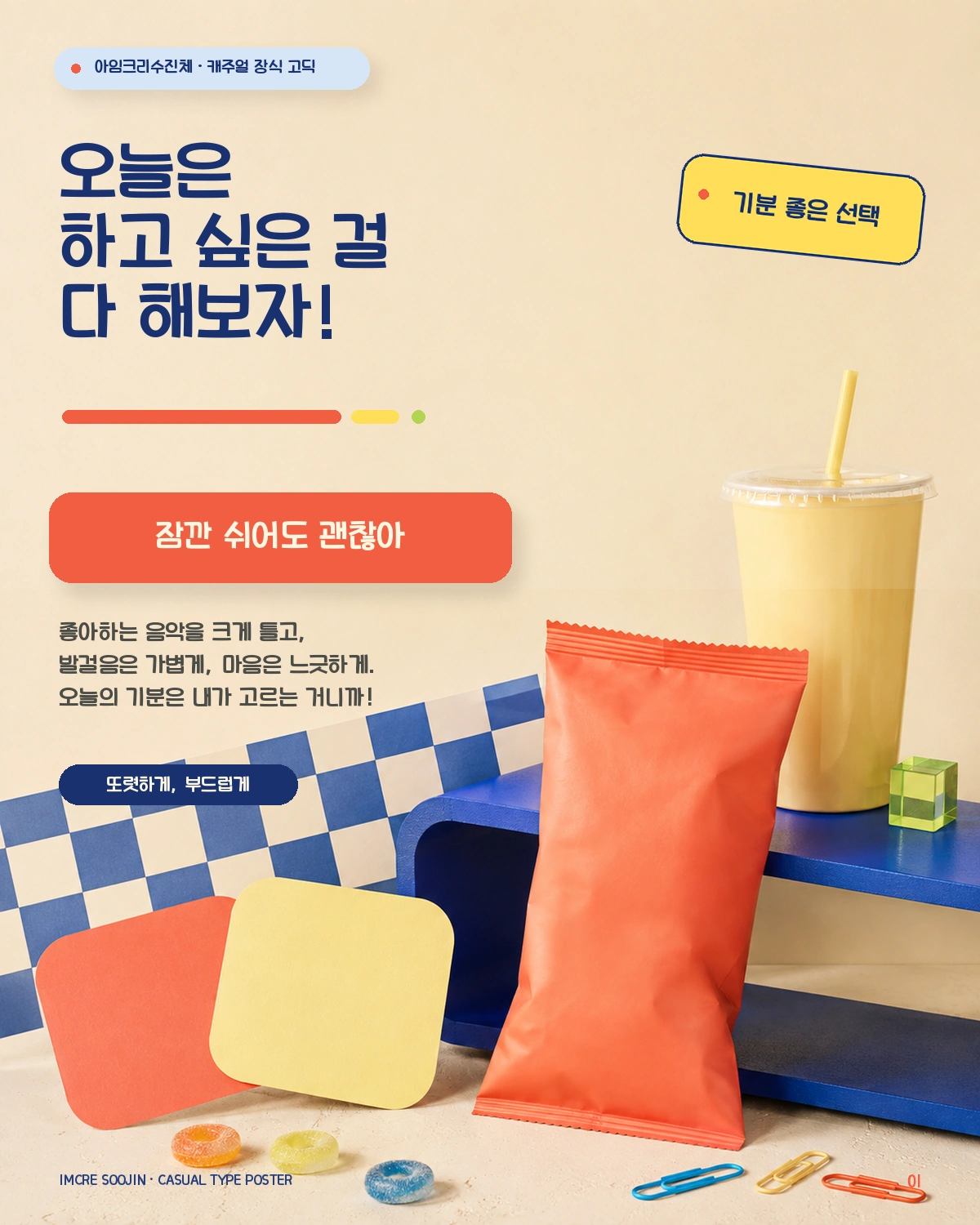
아임크리수진체 — 발렌타인드림에서 배포하는 무료 폰트입니다. 네모난 골격에 둥근 모서리를 더해 또렷하면서도 부드러운 인상을 주는 장식 고딕체
영상 디자인 스튜디오 발렌타인드림이 자사 앱의 전용서체로 만들어 2020년에 무료로 푼 서체입니다. 폰트 파일 안에는 저작권자가 발렌타인드림, 서체 설계는 와이즈폰트로 적혀 있습니다.
이름의 앞부분이 그 앱입니다. 아임크리는 I am Creator에서 온 이름으로, 유튜브 영상을 만들고 채널을 운영하는 법을 가르치는 교육 앱입니다. 출시 2주 만에 구글플레이 급상승 1위에 오른 것으로 알려져 있습니다. 뒷부분인 수진은 아임크리 프로젝트를 맡았던 담당자의 이름입니다. 앱 이름과 사람 이름을 나란히 붙인 셈입니다.
분류를 먼저 짚고 가야 합니다. 이름 때문에 손글씨로 짐작하기 쉬운데 **손글씨가 아니라 네모틀 고딕**입니다. 파일에서 재어 보면 받침이 붙어도 글자 높이가 거의 변하지 않고 낱자가 정사각형에 가까워, 여러 줄을 쌓아도 글줄이 가지런합니다.
조형에서 눈에 띄는 것은 마감입니다. ㅁ처럼 각진 자소의 모서리를 둥글게 굴렸고 ㅅ과 ㅈ의 획 끝도 둥글게 다듬어, 반듯한 골격에 부드러운 인상이 얹힙니다. 숫자에도 특징이 있어 1을 장식 없는 세로획 한 줄로 그렸습니다. 획 굵기는 중간쯤이라 크게 세워도 무겁지 않고 작게 줄여도 형태가 뭉개지지 않습니다.
굵기는 하나입니다. 현대 한글 11,172자를 모두 담아 어떤 글자를 넣어도 빠지지 않습니다. 제목이나 SNS 카드처럼 짧고 또렷하게 읽히는 자리에 맞고, 굵기가 하나뿐이라 위계가 여러 단계 필요한 긴 문서에는 한계가 있습니다. 인쇄와 웹사이트, 영상, 임베딩, 포장지는 물론 BI와 CI까지 상업적으로 쓸 수 있고, 폰트 파일을 고치는 것만 금지됩니다.